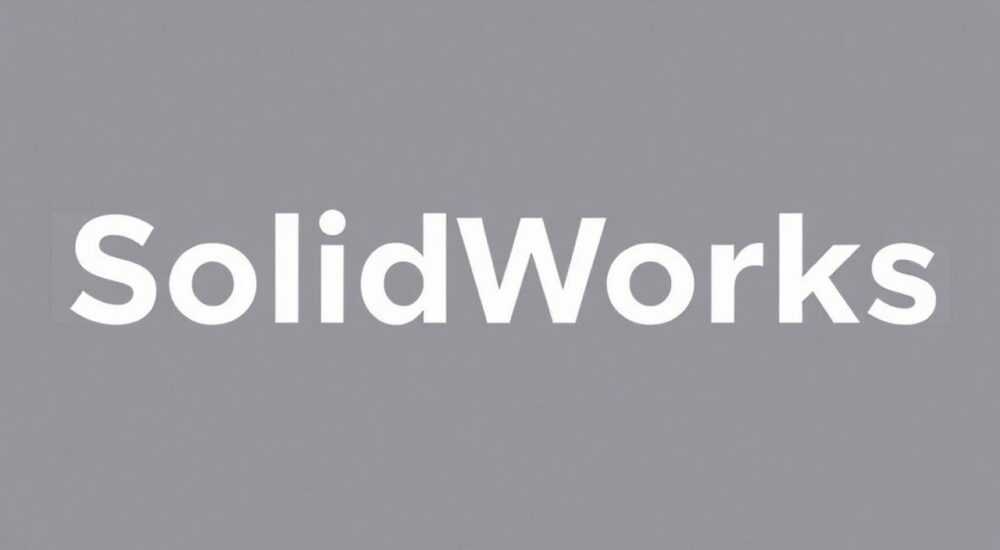
Как добавить шрифт в солид воркс
В SolidWorks возможность использовать нестандартные шрифты в чертежах, аннотациях и текстовых элементах модели играет важную роль при подготовке документации под требования ГОСТ, корпоративные стандарты или эстетические предпочтения. Однако система по умолчанию работает с ограниченным набором системных шрифтов, и добавление новых требует понимания как технических, так и программных аспектов интеграции. Проблема возникает особенно остро при переносе проектов между компьютерами — отсутствие нужного шрифта приводит к его замене на стандартный, что может повлиять на читаемость и соответствие нормативам.
Зачем добавлять шрифт в SolidWorks
Использование специализированных шрифтов в SolidWorks обусловлено как техническими, так и организационными требованиями. Например, в России и странах СНГ для оформления конструкторской документации согласно ГОСТ 2.304–81 требуется применение чертёжных шрифтов типа «Type A» или «Type B». Эти шрифты обеспечивают единообразие, легко читаются при масштабировании и подходят для автоматизированного распознавания. Без их применения чертежи могут быть отклонены при проверке или сертификации.
Кроме того, в крупных компаниях часто разрабатываются собственные корпоративные стили, включающие фирменные шрифты для маркировки, примечаний и заголовков. Это помогает стандартизировать документацию, упрощая её восприятие и контроль качества. Также дизайнеры и инженеры-конструкторы могут использовать декоративные шрифты при создании презентационных моделей, например, для логотипов на корпусах устройств.
Важно понимать, что выбор шрифта влияет не только на внешний вид, но и на производительность. Слишком сложные контурные шрифты (особенно TrueType с большим количеством узлов) могут замедлять работу программы при работе с большими сборками или множеством аннотаций. Поэтому оптимальный баланс между функциональностью и визуальной точностью — ключевой фактор при выборе шрифтовой политики в команде.
Как работают шрифты в SolidWorks
SolidWorks не является графическим редактором вроде Adobe Illustrator и не включает в себя встроенную базу шрифтов. Вместо этого программа обращается к шрифтам, установленным в операционной системе Windows. Это означает, что любой шрифт, доступный в списке шрифтов Windows (в папке C:WindowsFonts), автоматически становится доступным в SolidWorks после перезапуска приложения.
Форматы шрифтов, поддерживаемые SolidWorks, включают TrueType (.ttf) и OpenType (.otf). Оба формата хорошо поддерживаются современными версиями Windows и SolidWorks. Однако стоит учитывать, что некоторые OpenType-шрифты с продвинутыми функциями (например, ligatures, альтернативные глифы) могут отображаться некорректно, так как SolidWorks не всегда интерпретирует эти параметры.
При создании текста в чертежах, аннотациях, таблицах спецификаций или 3D-эскизах SolidWorks позволяет выбрать шрифт из выпадающего списка. Этот список динамически формируется на основе системных данных. Если шрифт был установлен во время работы программы, его нужно будет добавить вручную только после перезапуска SolidWorks.
- Установите шрифт в систему. Есть два способа:
- Перетащите файл шрифта в папку C:WindowsFonts.